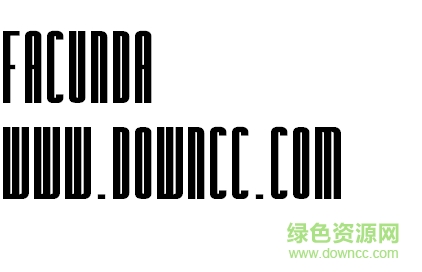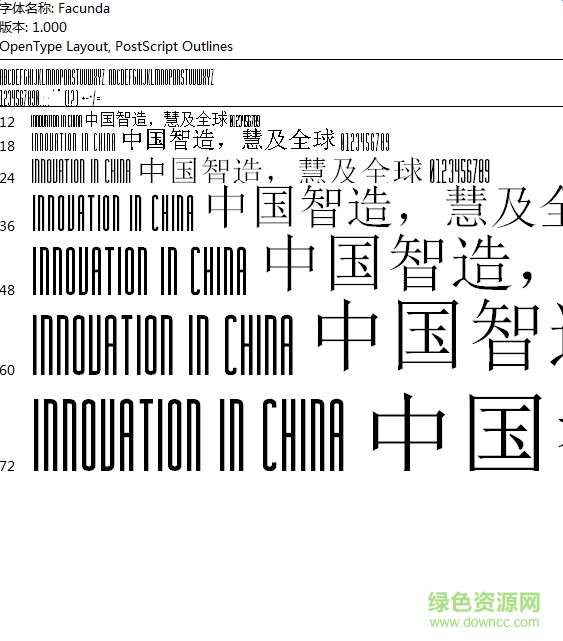
facunda字體是一款英文字體軟件,此字體筆畫豎長(zhǎng),創(chuàng)意十足,整體效果十分酷炫,可用于海報(bào)漫畫設(shè)計(jì)應(yīng)用,喜歡的朋友歡迎到綠色資源網(wǎng)下載體驗(yàn)!
facunda字體筆畫橫短豎長(zhǎng),給人古典優(yōu)雅的感覺,非主流氣息十足,綠色資源網(wǎng)為您提供綠色免費(fèi)的facunda字體下載!